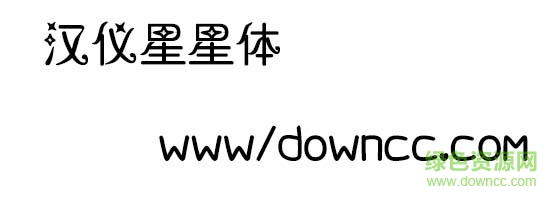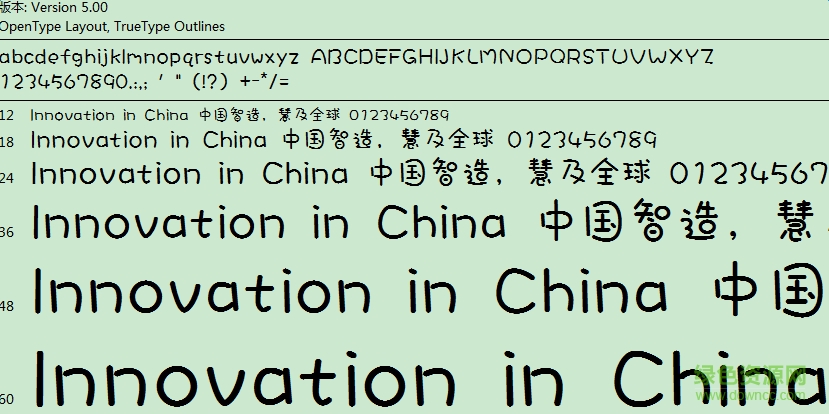
漢儀星星字體是一款漢儀字庫中的非常有特色的藝術(shù)字體,這款字體字形優(yōu)美,還有各種漂亮的星星圖案,非常適用于廣告設(shè)計(jì)、宣傳海報(bào)、ppt、影視制作等領(lǐng)域,喜歡的朋友歡迎來綠色資源網(wǎng)免費(fèi)下載使用。
漢儀星星字體是漢儀字體庫中的一款個(gè)性字體,該字體非常端莊大方,適用的范圍非常廣泛,有需要的朋友可以來綠色資源網(wǎng)下載使用!